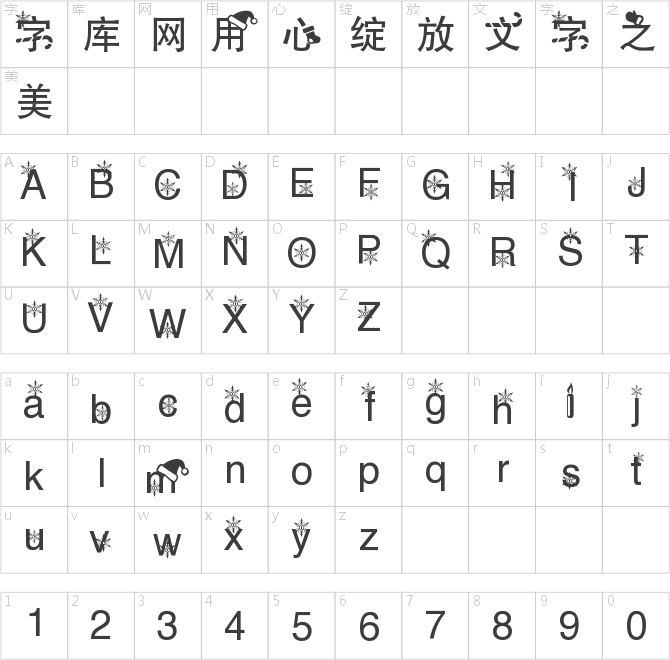
奇思圣誕節(jié)
奇思圣誕節(jié)字體圣誕節(jié)字庫(kù)是一款讓人賞心悅目、百看不厭的中文字體,適合各類廣告和產(chǎn)品包裝設(shè)計(jì)應(yīng)用,字體大小15.23MB,格式為ttf字體,上傳用戶是Aa字庫(kù),作者/版權(quán)方為奇思字庫(kù)